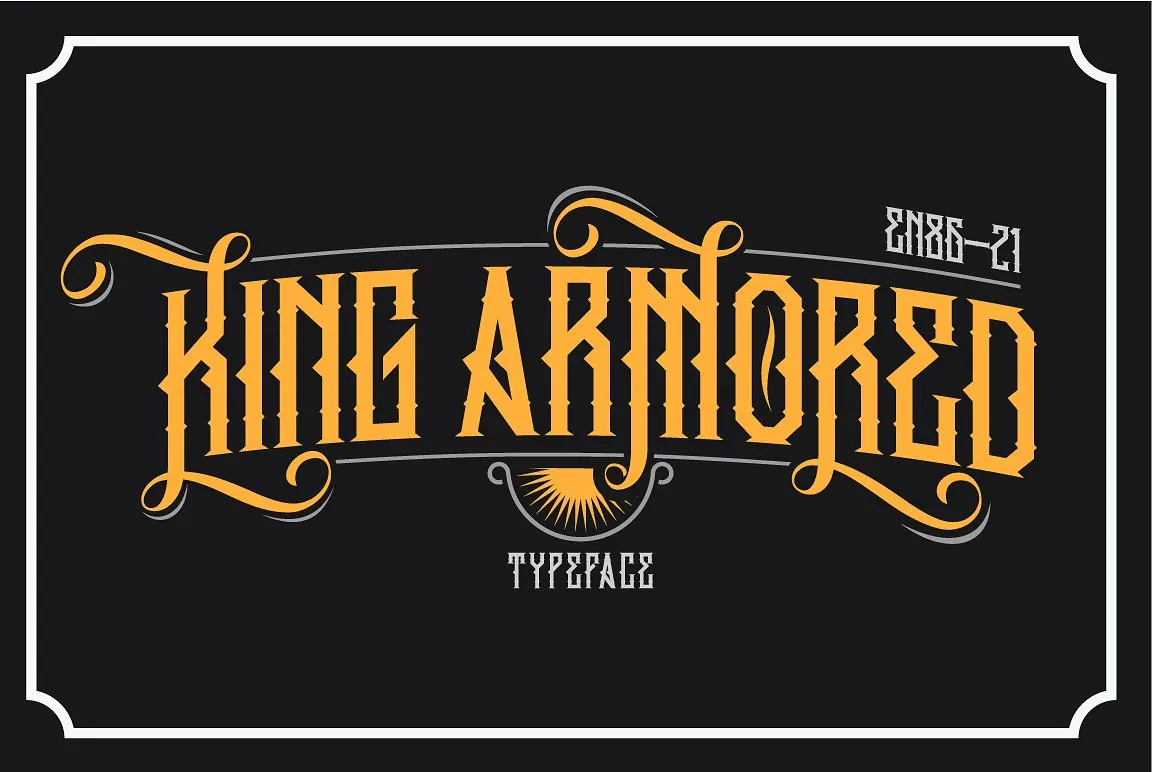
King Armored Typeface – Download Grátis
A fonte ‘King Armored Typeface’ é uma nova escolha perfeita para quem busca criar uma identidade visual única e diferenciada. Se você está procurando por uma fonte Blackletter para um novo projeto, a ‘King Armored Typeface’ surge como uma opção ideal que fará seu trabalho brilhar. Com sua tipografia impressionante e arrojada, esta fonte é perfeita para inviáveis de casamento ou blog. Ela também pode ser usada para criar logotipos incríveis ou belas molduras para a sua casa. Ou você pode simplesmente usar em pequenos negócios, capas de livros, embalagens de papelaria e muito mais. Você poderá fazer composições com esta fonte facilmente e de forma simples. O seu design elegante torna-a um recurso ideal não apenas para designers profissionais, mas também para iniciantes que desejam dar vida à sua obra.